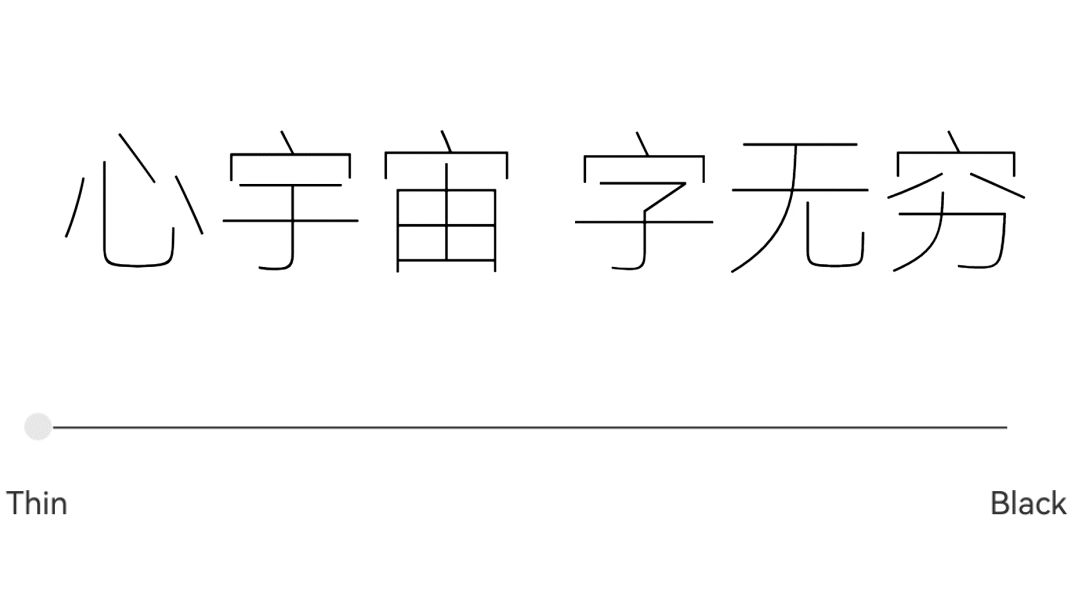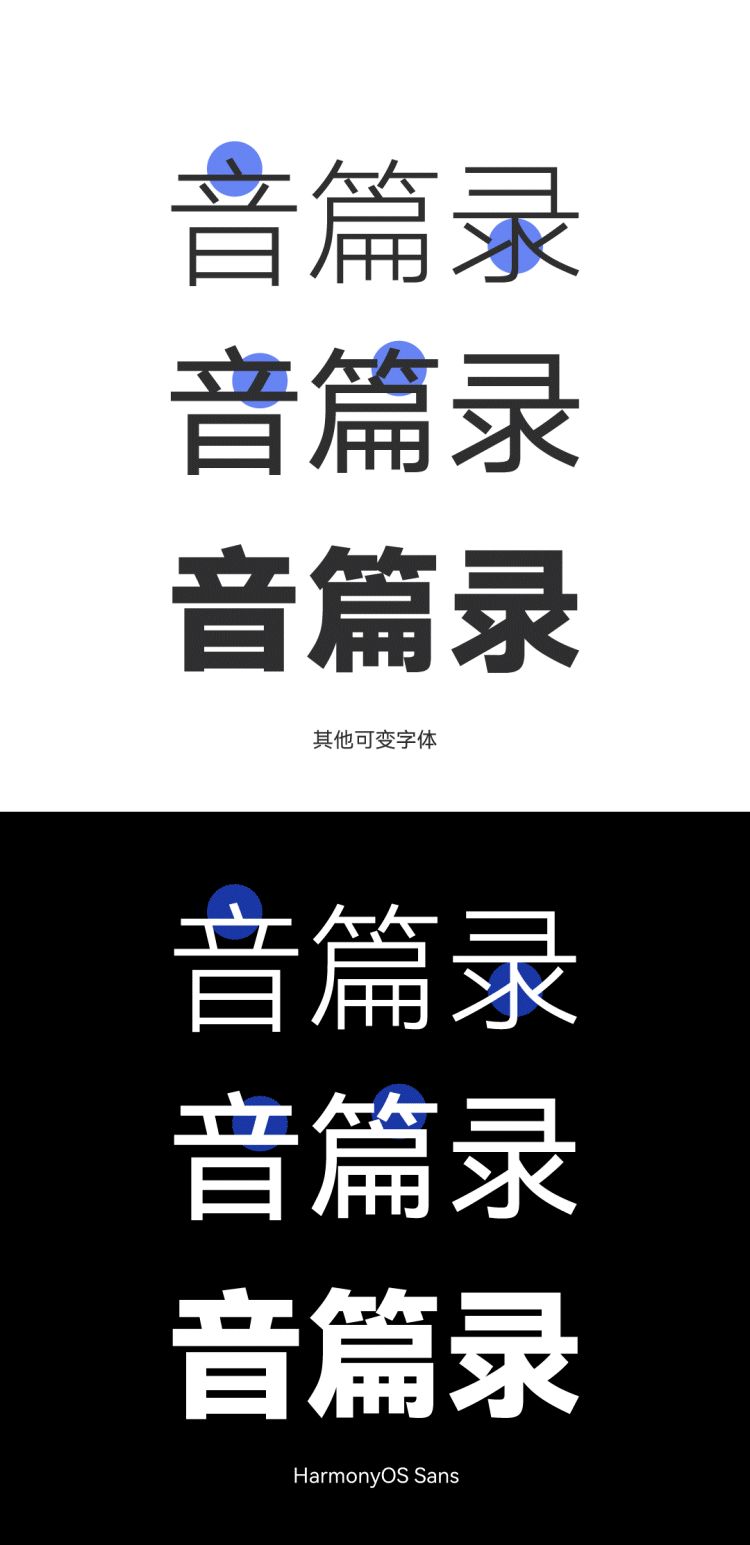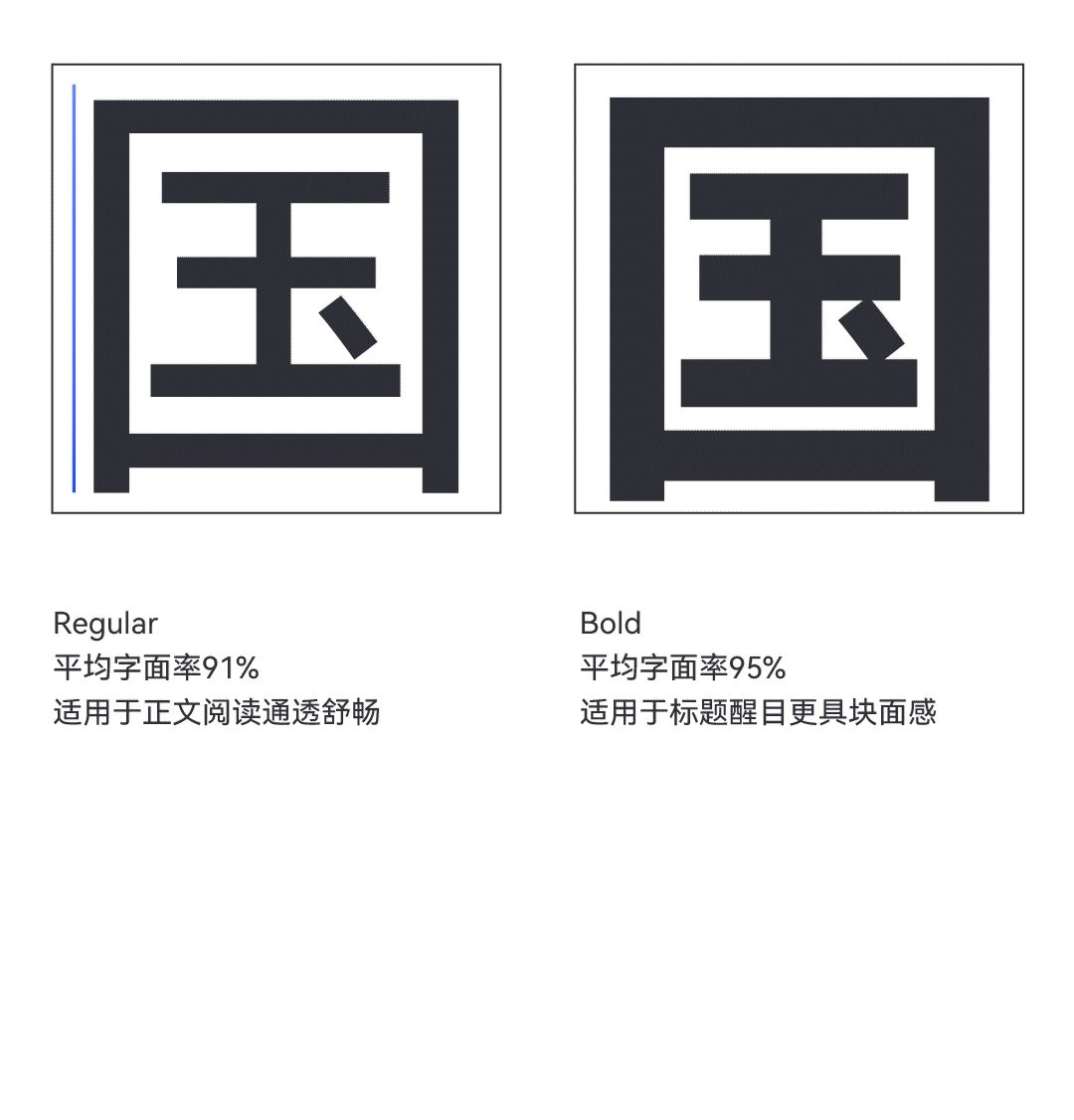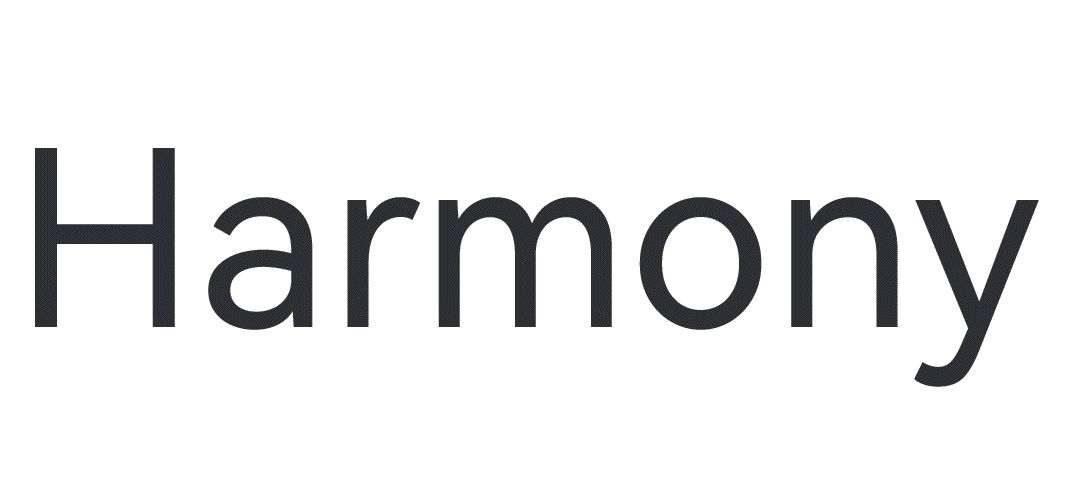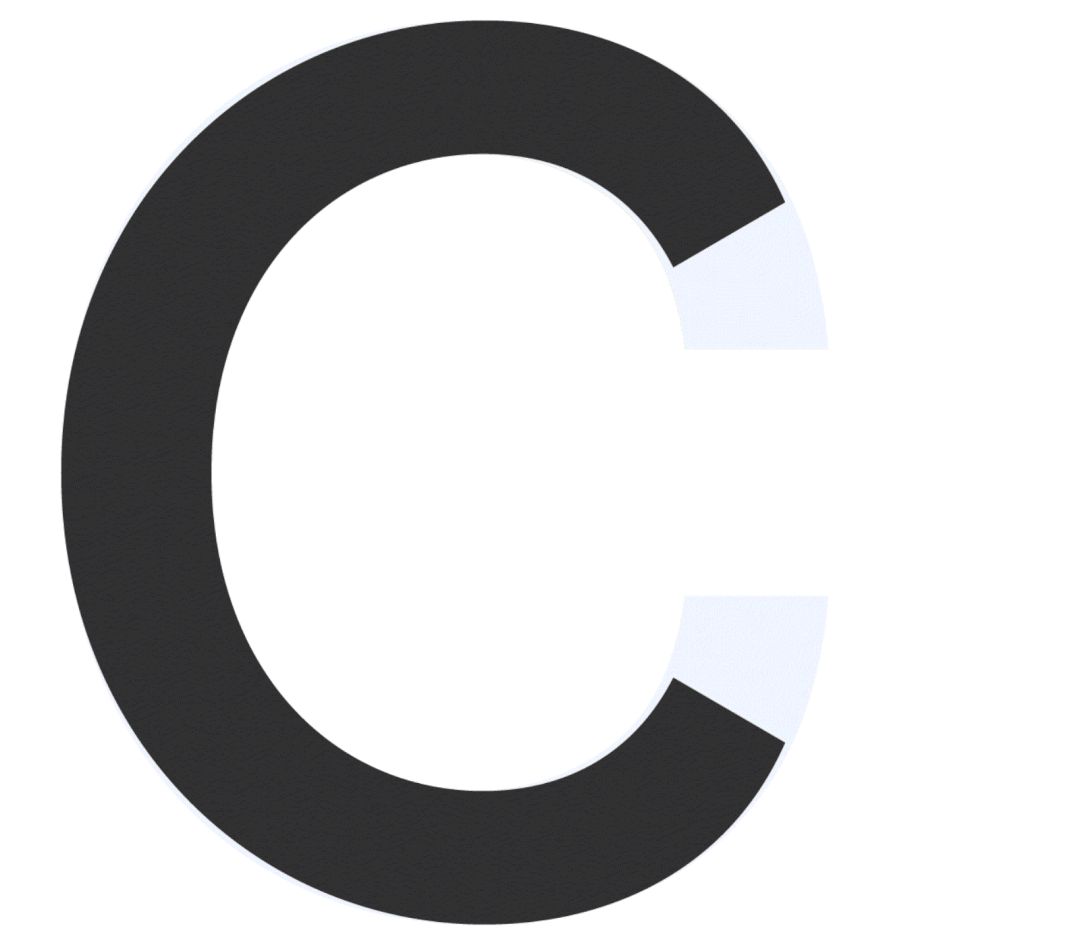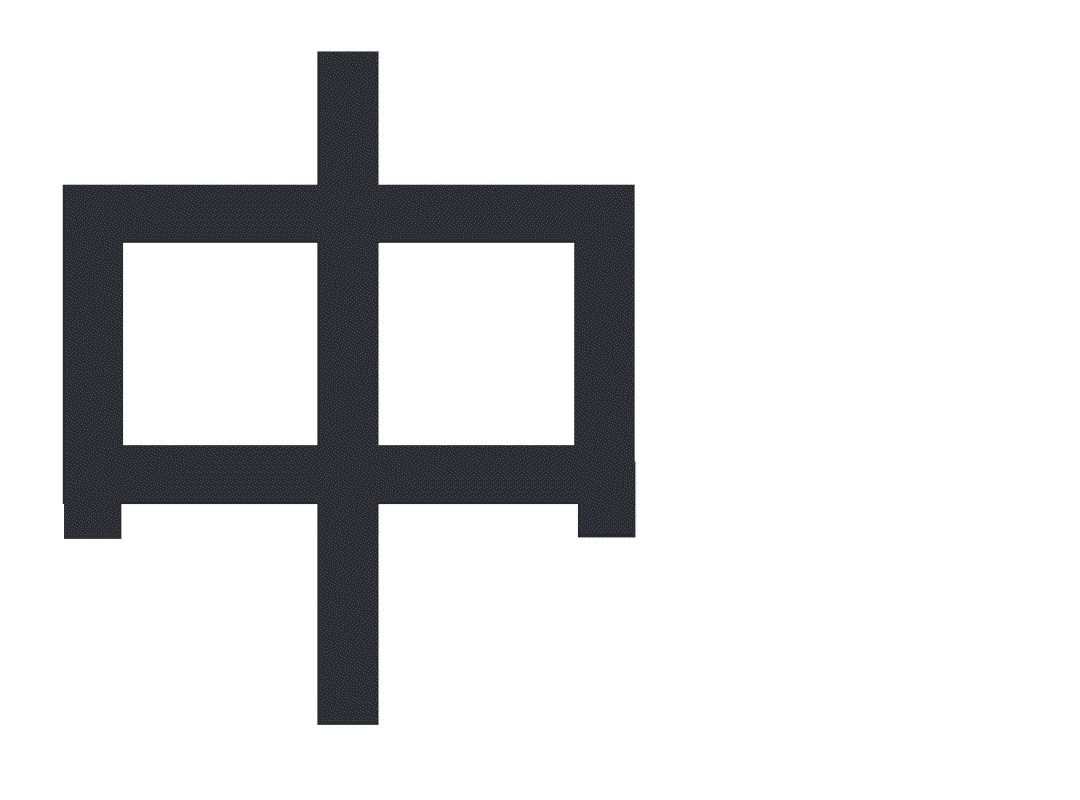
华为正式发布了HarmonyOS 2鸿蒙操作系统,其字体设计也是全新定制的“HarmonyOS Sans”,现已公开上线,鸿蒙字体可以免费商用。
该字体来自汉仪字库字体设计团队,设计上聚焦于功能性、普适性,是一款多语言的无级可变字体,支持简体中文、繁体中文、拉丁、西里尔、希腊、阿拉伯等5大书写系统,105种语言全球化覆盖。
HarmonyOS Sans字体的三大特性:
1、易读
系统字体区别于传统平面印刷字体,在智能终端的应用场景之中,易读是最基础也是最为关键的一个条件。
中文笔画复杂,HarmonyOS Sans在设计时为应对可变字体笔画连接处易破碎的情况,做出优化统一处理,使得字体最终呈现效果干净而利落。
繁琐的笔画、不均匀的布白,都会直接影响到用户的阅读,HarmonyOS Sans针对多元的应用场景对字体的“灰度”感受进行了优化。
根据用户不同的使用场景,字体的字面率做了差别化处理。
西文字形设计,为使用户能够快速读取信息,选用纯粹而经典的几何造型,直观醒目。
大开口造型处理,字形易认,辨识度更高。
在人因研究实验中,HarmonyOS Sans与优质的字体汉仪旗黑、微软雅黑进行了对比,眼动实验显示如下:
新字体平均注视时间要低于汉仪旗黑和微软雅黑。
西文与Product Sans、Roboto进行对比,新字体平均注视时间均低于其他字体,HarmonyOS Sans中西文得易读性均得到了印证。
2、独特
华为用户针对字形风格评价显示,用户评价高频词汇为:清晰的、中性的、优雅的、自然的、好看的、舒适的。
用户对新字体的好感度高于旧字体,且感知到了字体笔画的优化,如削弱了黑体的机械感等。
中文“口”部件,现代感结构处理。
笔画造型,融入了书写美感。
在保障字体功能的前提下,相较其他系统字体,HarmonyOS Sans的独特是在人文感和现代感中找到了新的平衡。
传统几何结构通常易读性较差,为了规避此类问题,在设计西文时,减少了字形宽度比例差异。
“Italic” 的设计参考了手写字的笔画结构,向历史致敬。
3、通用
除多种书写系统的文字匹配,文字与符号、图标甚至是手机系统之间的匹配,都会直接影响到用户的体验,华为的全球化视野,以及多元复杂的应用场景,注定了HarmonyOS Sans必须具备极强的通用性。
在人因研究过程中,西文的用户体验和可读性研究反馈出一个十分有趣的现象,当用户从系统默认字体Roboto变为HarmonyOS Sans时不会觉得很跳跃,但从HarmonyOS Sans变为Roboto时,体验感明显下降。
为应对中西文匹配排版,时常不甚协调的问题,HarmonyOS Sans做出了针对性优化。从整体来看,HarmonyOS Sans比Roboto更显大更显宽,与中文匹配度更高。
HarmonyOS Sans还设计了 Italic、Condensed、Condensed Italic字体,为多元复杂的应用场景提供了更多的可能性。
为满足用户的不同的使用场景,HarmonyOS Sans对符号设定了多种与文字相匹配的排版属性。
在实际应用层面,文字与系统的匹配是不可忽视的一环,HarmonyOS Sans逐一细化用户的使用场景,并作出针对化处理。
人因研究结果显示,相同字重下,深色背景感知文字更粗。
为此,深色模式下使用了更细的字重,让字体的视觉粗细与浅色模式保持一致。
文字与图标使用统一的设计语言,也是为用户呈现多设备互助全新体验的关键要素,HarmonyOS Sans最终呈现如下: